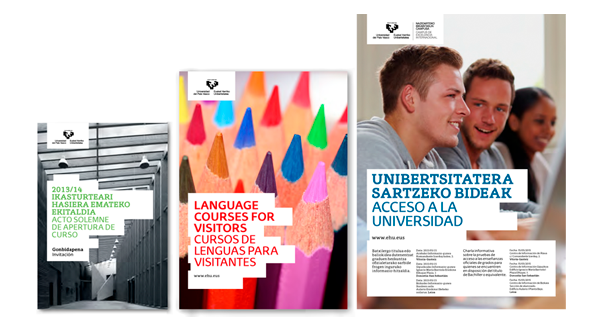
Texto y tipografía
Redacción del mensaje en el sistema gráfico UPV/EHU.
Portada del folleto de Acceso a la Universidad
La forma en que escribimos determina nuestro estilo. Por eso, el texto y la forma de redactarlo son parte fundamental de un sistema gráfico, porque determina un estilo visual y comunica de forma correcta y coherente.
El texto es el canal de información más directo de la composición y por ello debemos cuidar la forma en que se comunican nuestros mensajes.
Utilizaremos nuestra tipografía corporativa EHU en todos los materiales de comunicación, tal y como se indica en las siguientes páginas.
Tipografía
EHU tipografia: EHUSerif eta EHUSans
Nuestra tipografía principal
La familia tipográfica EHU diseñada por el equipo de tipógrafos de UPV/EHU es nuestra fuente corporativa. Esta tipografía ha sido diseñada especialmente para esta nueva expresión de la marca UPV/EHU. Cuenta con dos versiones (Serif y Sans). Cada versión cuenta con tres pesos —Bold, Regular y Serif— para poder preparar apropiadamente los diferentes elementos de diseño.
Arial tipografia
Tipografía de sustitución
Se ubica a partir del margen de 10,863 mm en la zona superior izquierda de los formatos DIN A5 y A4. Este espacio se reserva únicamente para los espacios que llevan las marcas, exceptuando en los casos especiales mencionados. Se reserva el resto del espacio por debajo del logotipo y el margen de seguridad, para la creación de las Cajas Espacios contenedoras de textos.
Composición de los titulares
Ejemplo de dos portadas
Dentro de nuestro sistema utilizamos un estilo: a la hora de tratar los textos de las portadas, las piezas informativas principales y los titulares de textos en general irán siempre colocados dentro de la Caja Espacio con un margen generoso e irregular, se alinearán a la izquierda y no se cortarán con guiones.
El titular irá escrito en mayúsculas y deberá ser corto, no más de 7-8 palabras aproximadamente. Cuando supere las 7-8 palabras se reducirá proporcionalmente el cuerpo de texto.
Habrá titulares que puedan entrar en una línea, pero por motivos de composición y diseño, se optará por dividir el titular de cada idioma en cinco líneas como máximo, utilizando preferiblemente saltos de línea cada dos o tres palabras.
Los titulares principales
Dos ejemplos de titulares, el primero con una longitud adecuada y el segundo con una longitud excesiva
Se recomienda el uso de titulares que como límite tengan 7 y 8 palabras, entre las cuales figuren artículos y preposiciones. No se recomiendan titulares que excedan esta proporción porque competirán visualmente con el recurso visual que ilustra el mensaje.
Caja alta y baja
Ejemplo de como utilizar la caja alta para titulares y la caja baja para texto
Utilizamos caja alta para los titulares principales y caja baja para los textos de contenido secundarios (b).
Kerning e interlineado
A la hora de componer los títulos y subtítulos, habrá que tener en cuenta el kerning.
En los documentos monolingües el kerning será de 0 en los titulares y subtitulares que irán en caja alta en EHUSerif u óptico de -10 los textos de contenido.
En el caso de los documentos bilingües y trilingües, el kerning es óptico de -25 para los titulares en EHUSans para el segundo idioma. Esto nos dará las claves para presentar cada información de manera clara y consistente (a) (b).
Texto y tipografía - Alineación textos
Alineación de los textos en las portadas
Ejemplo de alineación del título debajo del logotipo
Todos los textos (titulares, subtítulos, página web, textos informativos… de las portadas) van alineados verticalmente a la izquierda con el logotipo de la Universidad siempre y cuando sea posible.
Texto y tipografia - Documentos monolingües - Tipografía
Documentos monolingües. Tipografía para datos de portadas
Portada de un documento monolingüe
Vamos a utilizar la tipografía EHU en la versión Serif que ha sido diseñada como la versión principal de este sistema gráfico. La versión Serif tiene una estética de la semejanza y la vecindad de referentes comunes con la obra de Eduardo Chillida. En sus obras refleja que la construcción de formas supone una constante lucha contra la ortogonalidad y la simetría. La versión Serif refleja la intención que hay en la obra del escultor por desplazar el rigor o la frialdad del ángulo recto hacia formas ligeramente obtusas o agudas, dando respuestas espacialmente más ricas en cuanto a expresión visual.
Los diferentes pesos de esta versión los vamos a utilizar de la siguiente manera:
Dos portadas muestran como utilizar los diferentes pesos de la tipografía
Texto y tipografía - Documentos monolingües - Tamaños de tipografías
Documentos monolingües. Tamaños de tipografías
Tres portadas con diferentes diseños
Aplicaciones no válidas
Ejemplos de malas prácticas
1. No usar tipografías alternativas
2. No utilizar textos verticales ni inclinados.
3. No rodear con el texto ninguna forma.
4. No introducir el texto en otra forma que no sea las Cajas Espacio.
5. No distorsionar la tipografía comprimiéndola, estirándola o deformándola.
6. No aplicar efectos visuales a la tipografía como sombras, desenfoques, etc…
7. No utilizar la versión Outline de la tipografía.
8. No centrar ni alinear el texto de ningún otro modo que no sean a la izquierda.